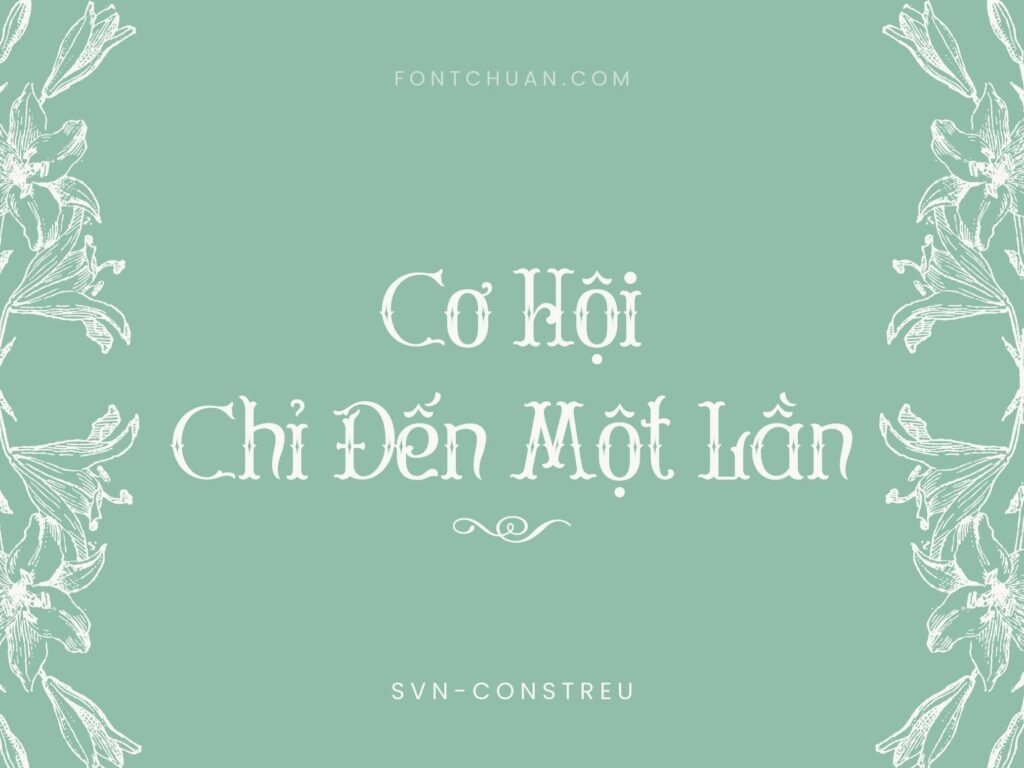
Font SVN Constreu Việt Hóa
Constreu là một font chữ mang phong cách Victorian cổ điển, được thiết kế bởi TypeAliens. Font này có kiểu dáng đơn giản, không quá nhiều chi tiết trang trí trên cấu trúc chữ, tạo nên sự tinh tế và dễ nhìn. Constreu đã được Việt hóa để hỗ trợ tiếng Việt bởi Styleno.1 Fonts, đồng thời hỗ trợ nhiều ngôn ngữ khác, giúp mở rộng phạm vi sử dụng trên toàn cầu. Font này được thành viên của Font Chuẩn sưu tầm và chia sẻ, đáp ứng nhu cầu của bạn đọc và ứng dụng thực tế vào các dự án thiết kế.
Đặc điểm thiết kế của Constreu bao gồm các đường nét cổ điển với cấu trúc chữ đơn giản, phù hợp cho các thiết kế vintage như logo, logotype, thiết kế thẻ bài, huy hiệu, nhãn hiệu rượu, xây dựng thương hiệu và quảng cáo. Các ngành nghề phù hợp bao gồm quảng cáo, nghệ thuật và thiết kế đồ họa.